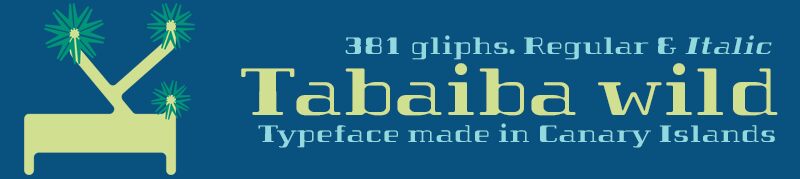
Tabaiba wild ffp Italic
Tabaiba wild es mi ltima fuente hecha antes de irme de las Islas Canarias, es una mezcla de fuente techno y dec con slab serifs redondeados para diseo grfico
Tabaiba wild is my ultimate font made before leaving the Canary Islands, is a mixture of techno and Deco font with rounded slab serifs for graphic design.
TipografÌa tecno decÛ con slab serif para carteles, posters o publicaciones.